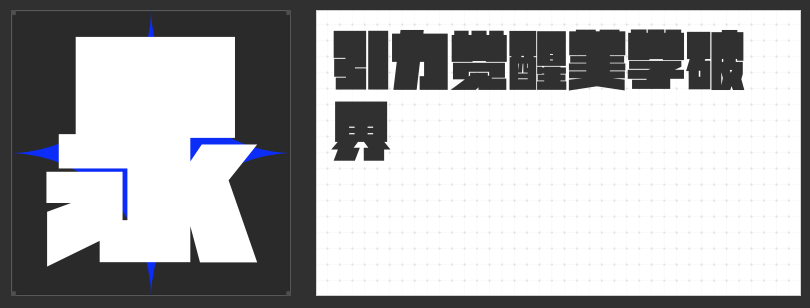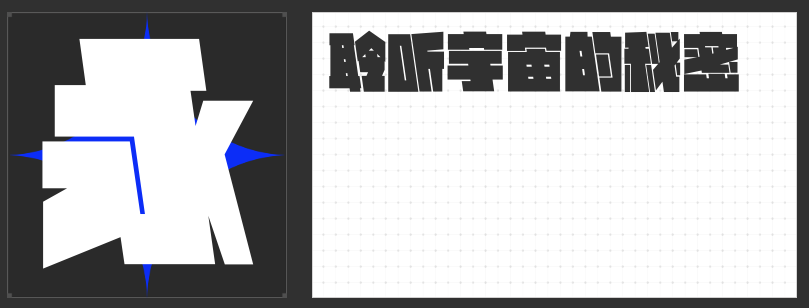
探索粗体字体的无限魅力:粗体字推荐
在视觉设计的广阔天地里,粗体字以其独特的魅力,成为传递力量、强调信息与营造氛围的得力工具。它们不仅承载着文字的基本功能,更以鲜明的形态美学,为设计作品增添一抹不可忽视的视觉焦点。今天,就让我们一同探索几款在视觉美学上独树一帜的粗体字推荐,感受它们如何在设计中熠熠生辉。
励字逆反差圆舞简 超级黑:力量与优雅的完美碰撞
励字逆反差圆舞简 超级黑独特的逆反差设计,让每一个字都仿佛跃然纸上,充满力量与动感。笔画转折处的弧线处理又赋予了字体一种流畅与柔美,超级黑的字重更是加深了这种视觉冲击力。无论是用于标题、海报还是品牌标识,励字逆反差圆舞简 超级黑都能以其独特的魅力,瞬间吸引眼球,传递出强烈而深邃的视觉信息。
励字铁拳简 超级黑:刚劲之美的典范
励字铁拳简 超级黑,一款彰显刚劲之美的字体力作。其笔画粗犷有力,如同铁拳出击,每一笔都透露出坚不可摧的力量感。超级黑的字重加深了这种视觉震撼,使励字铁拳简 超级黑在任何设计中都能成为焦点。无论是用于激励人心的标语、硬朗风格的广告,还是展现力量与决心的品牌形象,励字铁拳简 超级黑都能完美诠释,让人过目难忘。
励字大头黑简 超级黑:醒目与力量的双重奏
励字大头黑简 超级黑,一款以醒目与力量著称的字体。其设计巧妙地将字头放大,结合超级黑的深邃色彩,营造出强烈的视觉冲击力。每一笔都如同重锤击鼓,铿锵有力,让人一眼难忘。无论是用于震撼人心的海报标题,还是需要突出重点的文本设计,励字大头黑简 超级黑都能完美胜任,彰显不凡气质。
励字飞行黑简 超级黑:速度与激情的视觉盛宴
励字飞行黑简 超级黑其独特的视觉设计,仿佛文字在纸面上自由飞翔,展现出一种速度的动感美,让每一个字都充满力量与活力。无论是用于动感十足的海报设计,还是追求速度与效率的品牌标识,励字飞行黑简 超级黑都能完美诠释,引领视觉潮流。
粗体字体以其独特的魅力和无限的创意空间,在设计中发挥着不可替代的作用。无论是追求视觉震撼、简约现代还是温馨亲切的设计风格,总有一款粗体创意字体能够满足你的需求。让我们一起探索这些字体的无限可能,为设计作品增添更多的创意与个性吧!